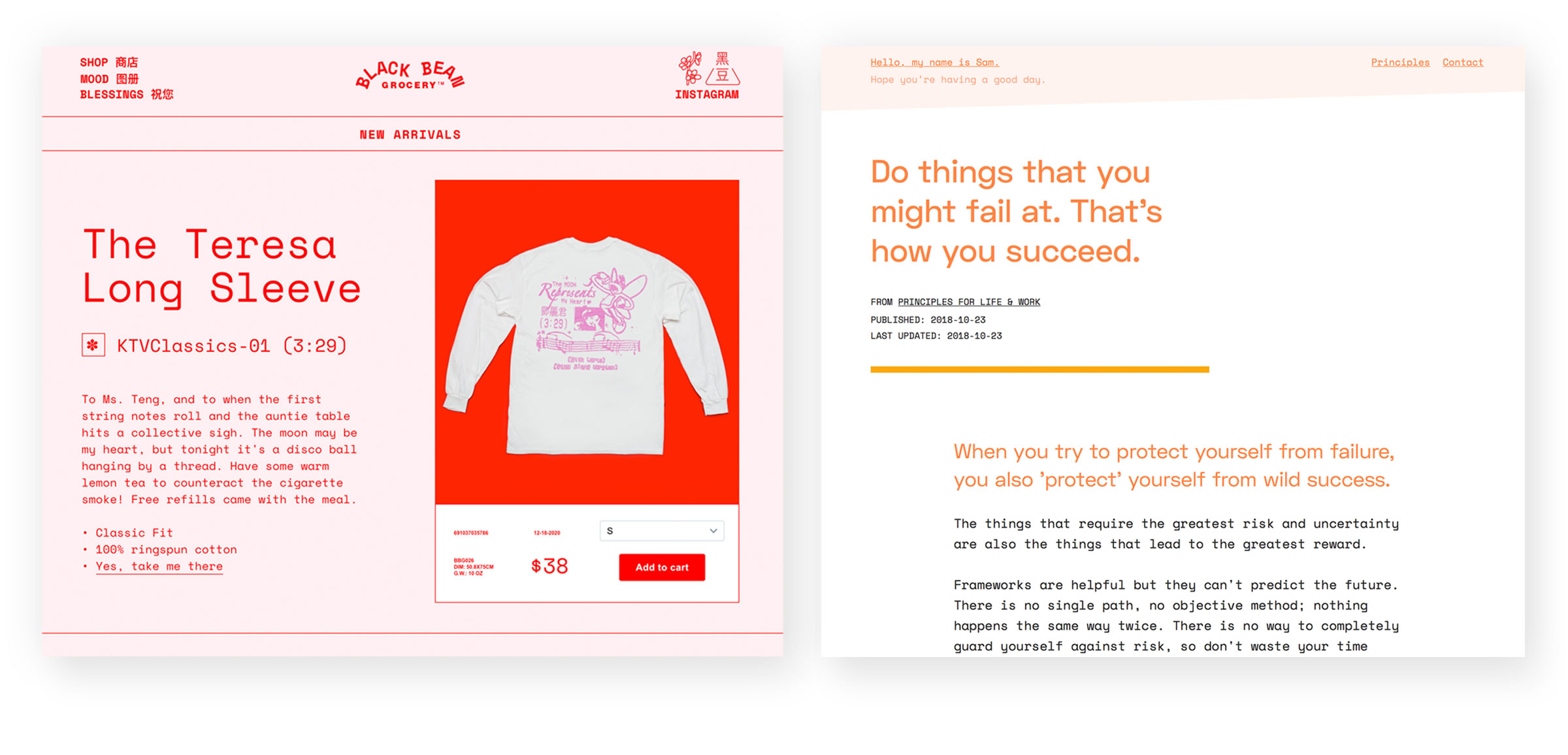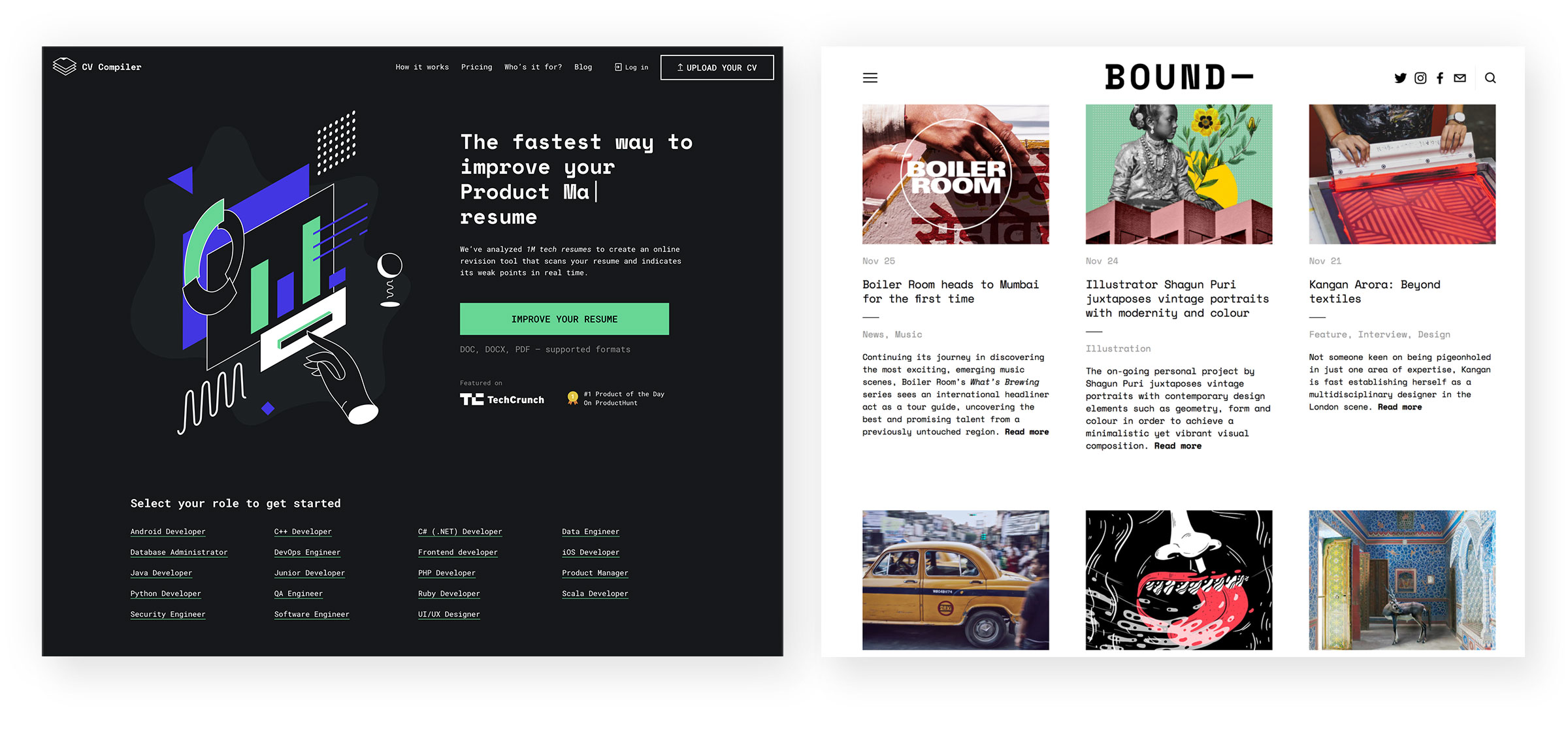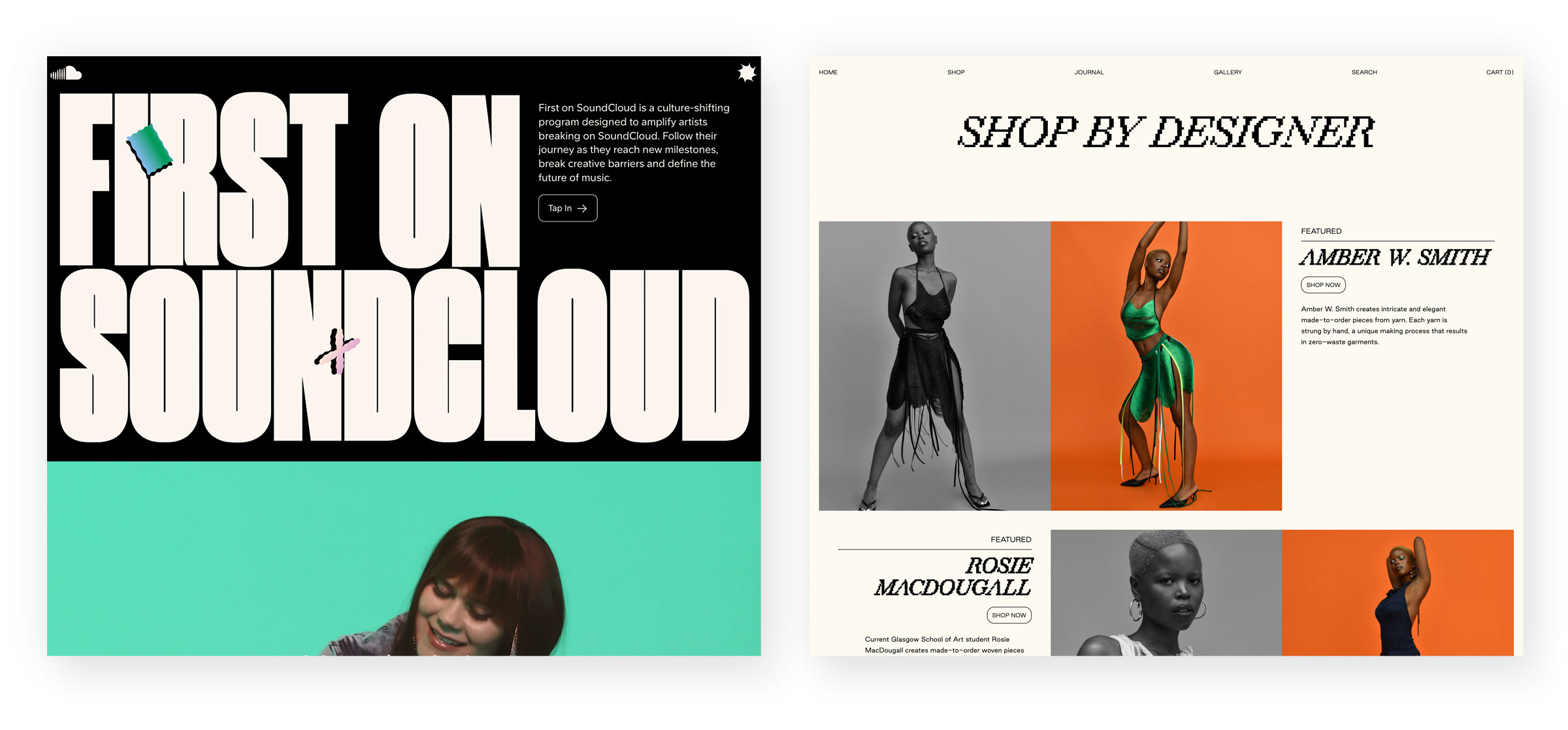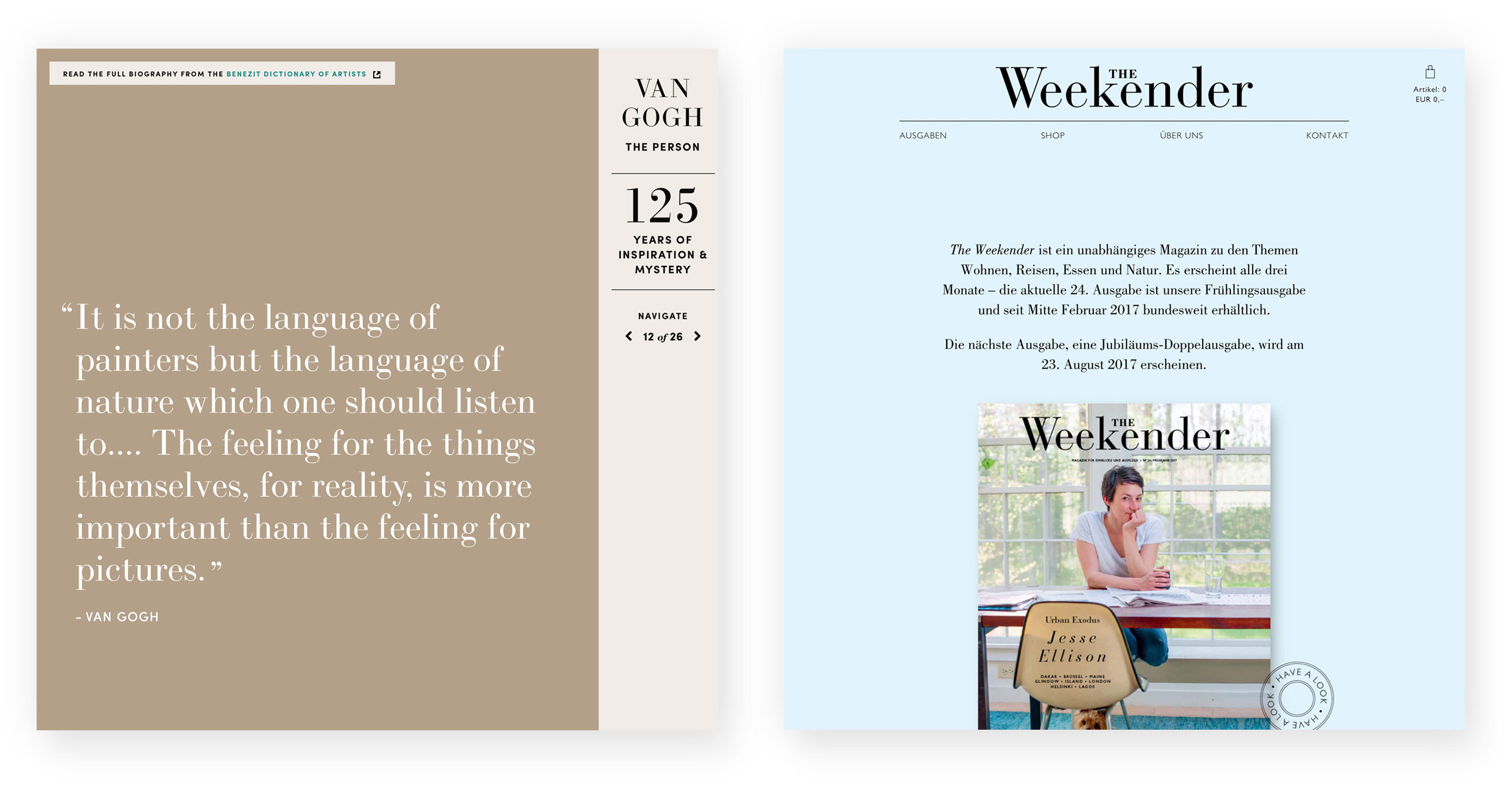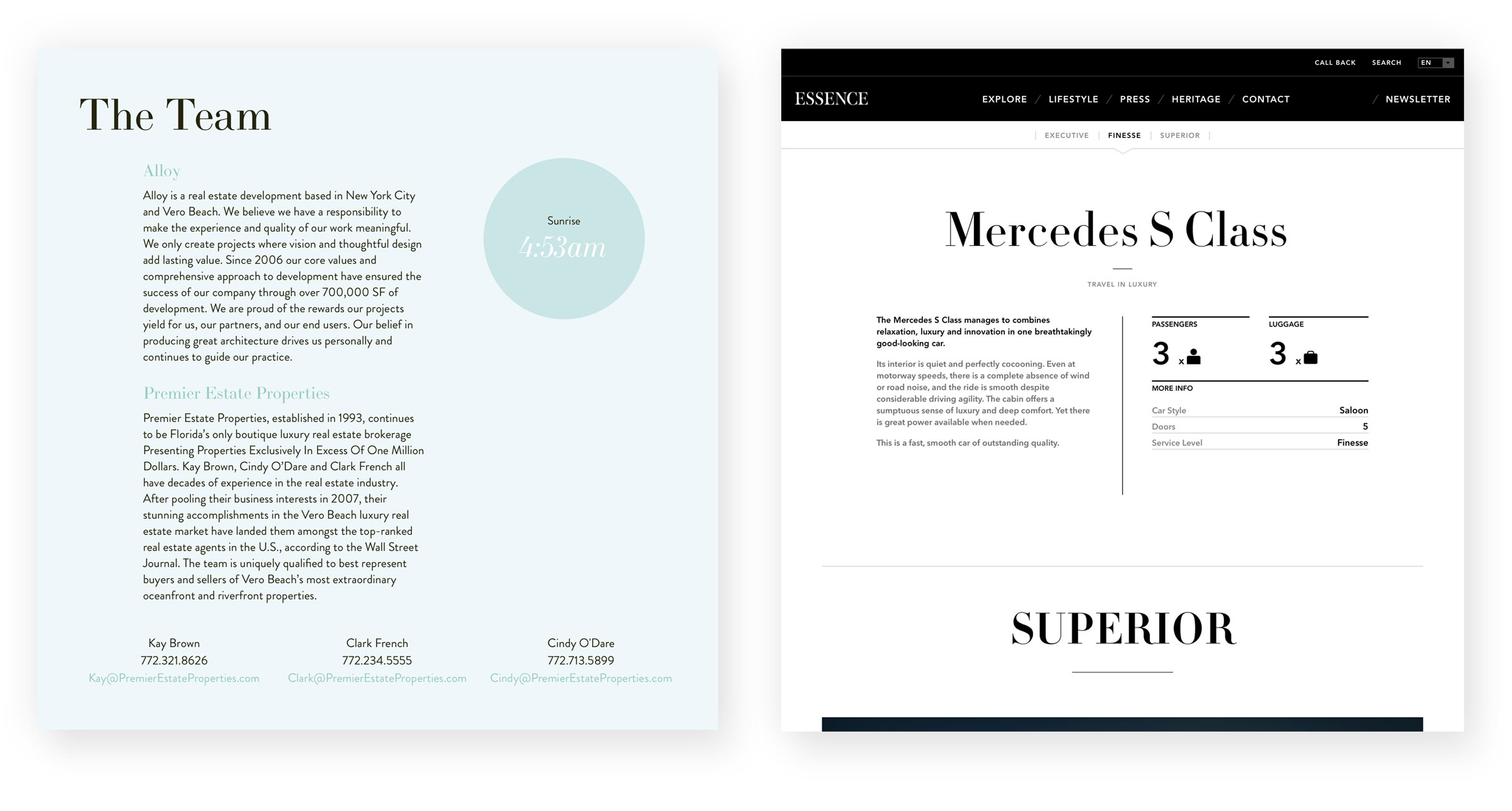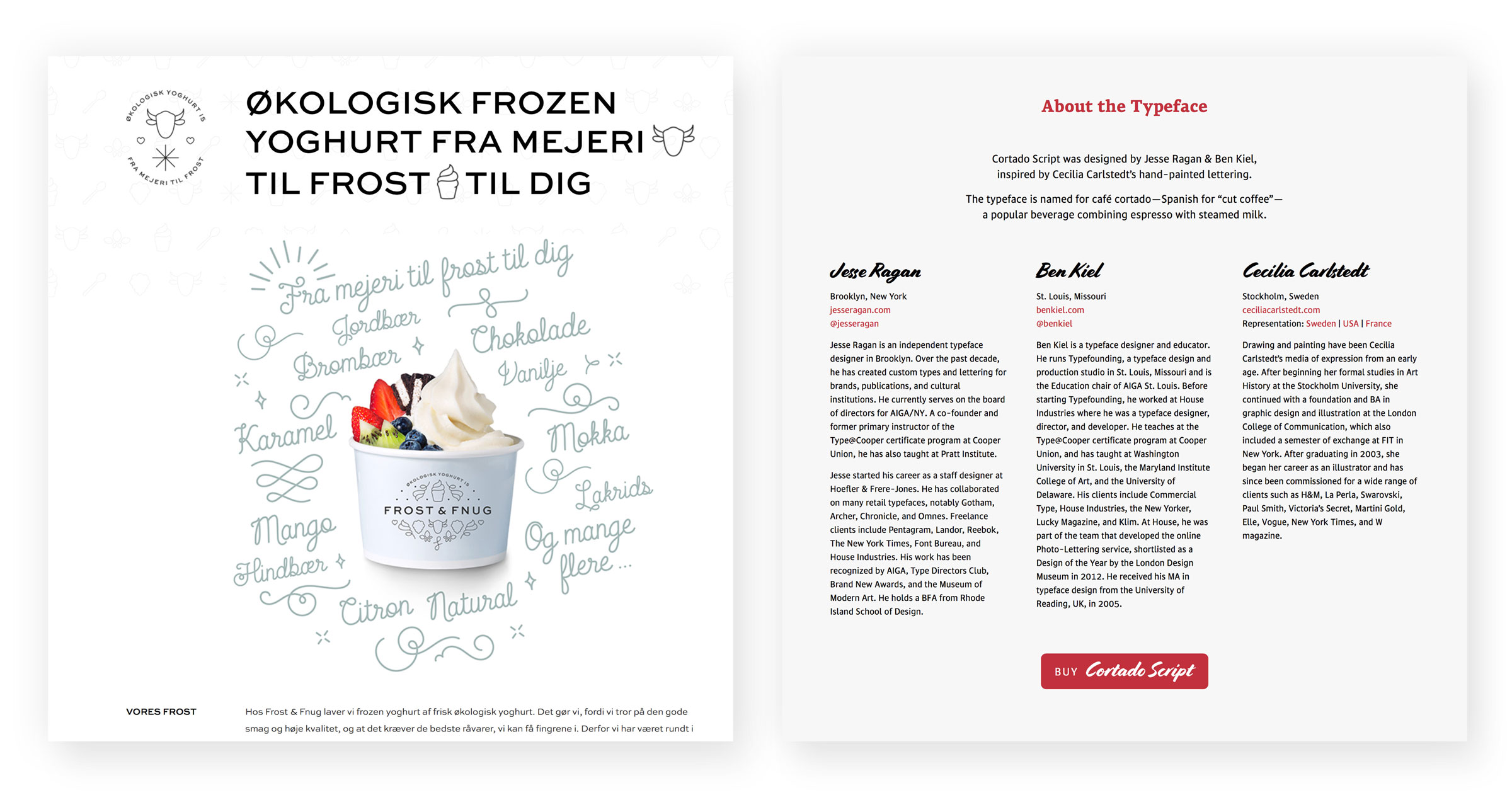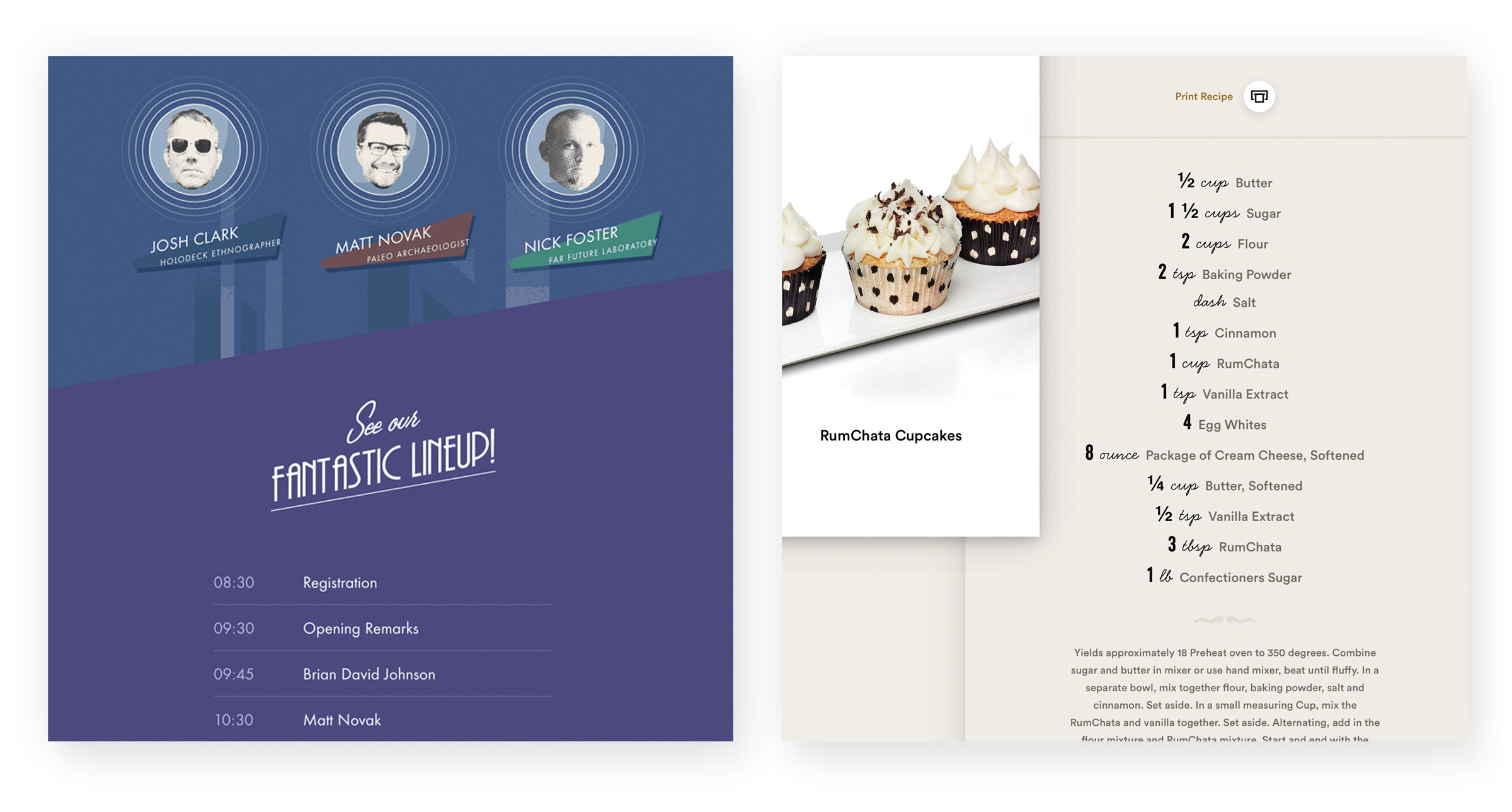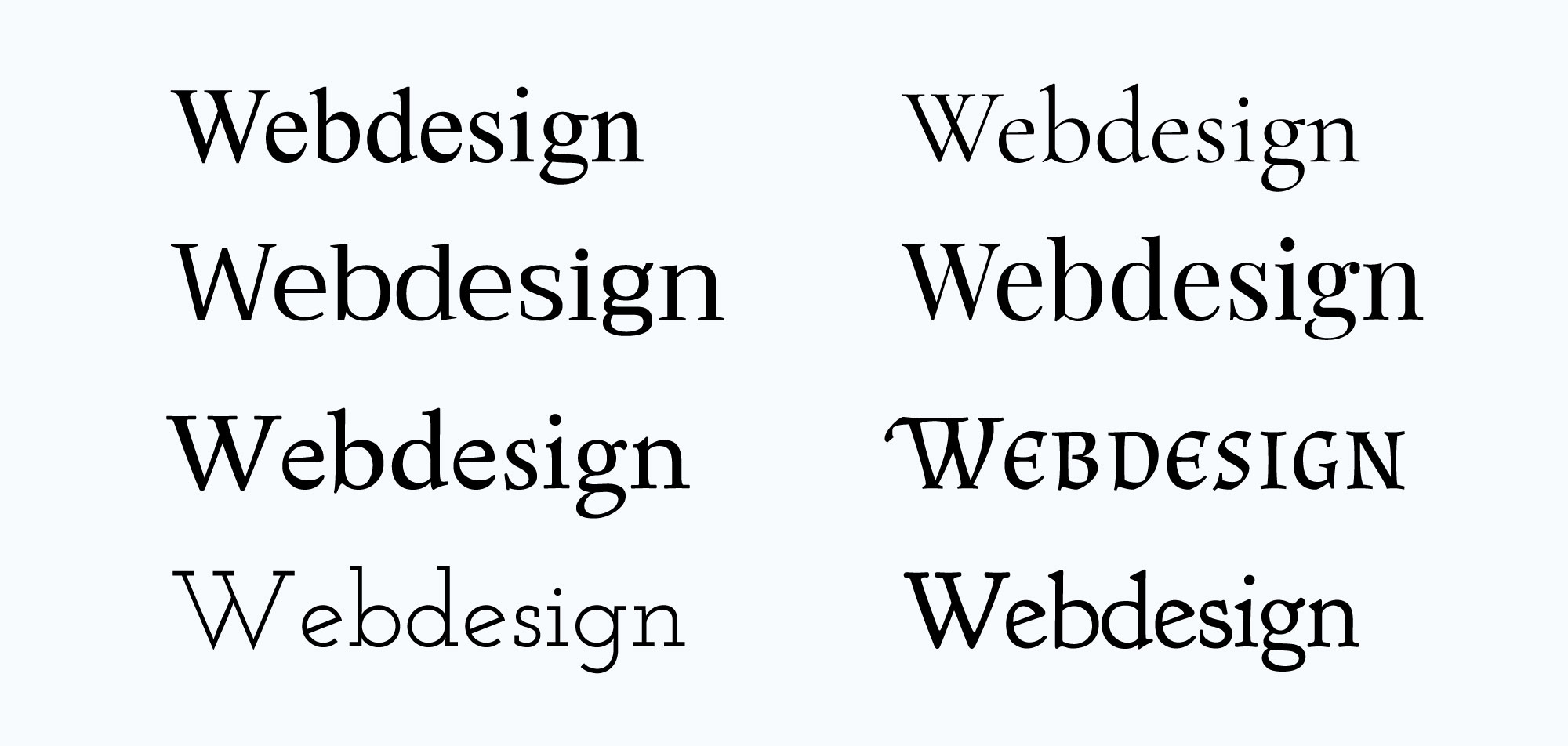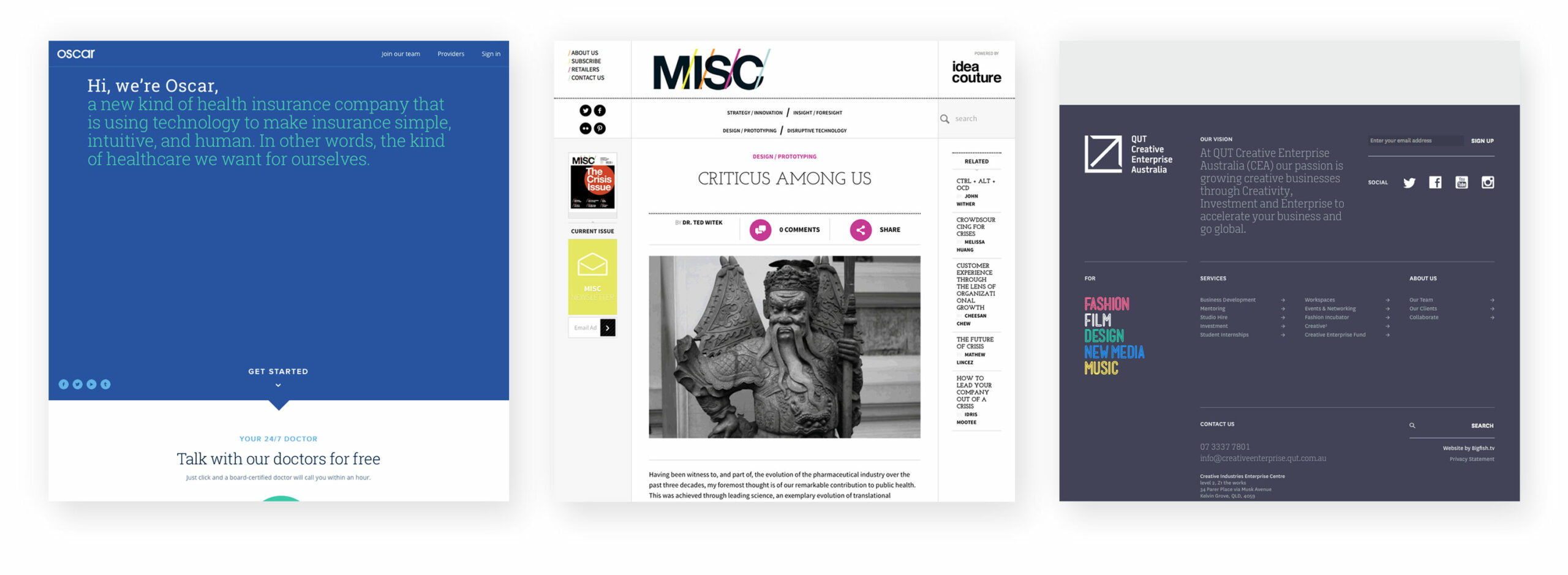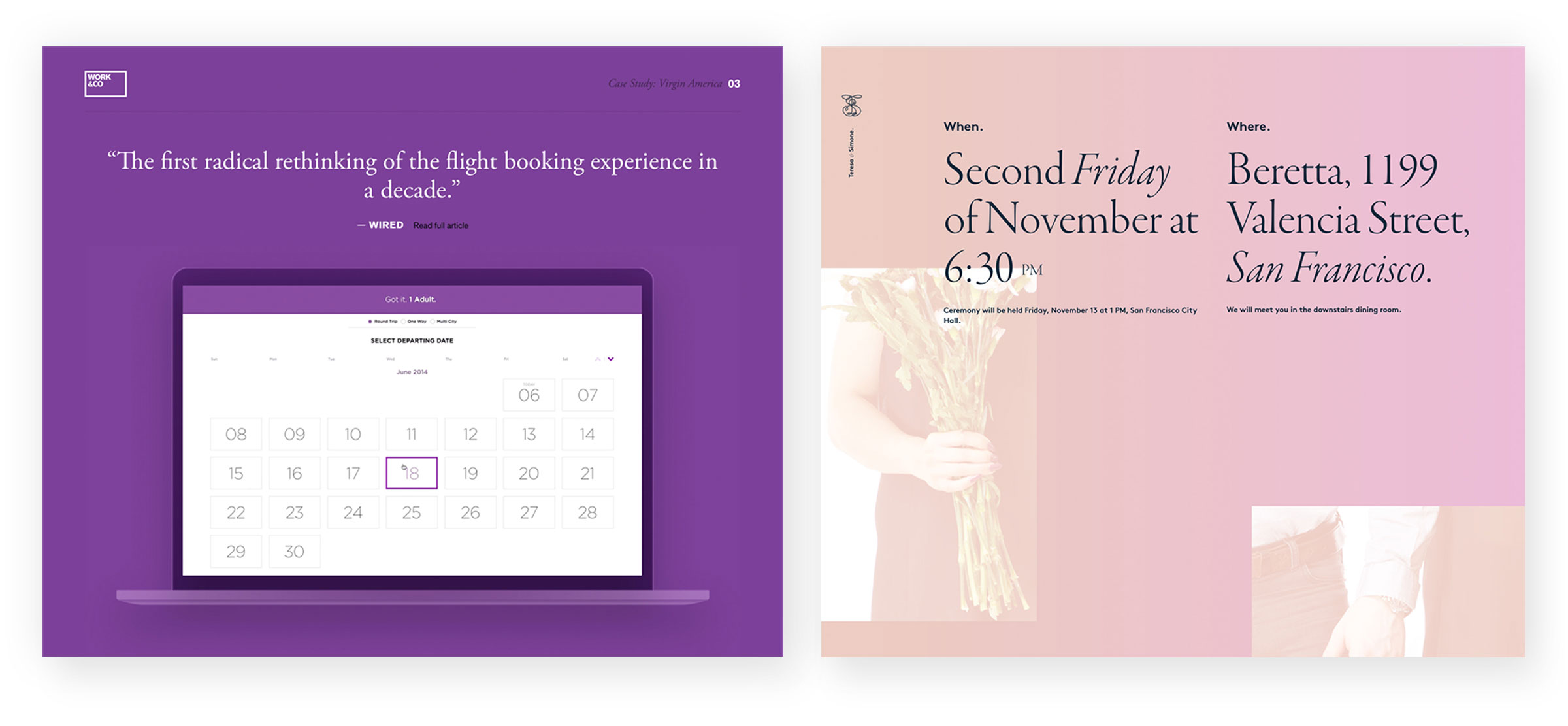
Der ausführliche Überblick
Schriftarten
Auf dieser Seite bekommst du einen umfangreichen Einblick in Schriftarten und deren Einteilung. Ich zeige dir  Einsatzgebiete und viele Beispiele. Zusätzlich erfährst du u. a., wo man Schriftarten finden und identifizieren kann.
Es gibt zigtausende Schriftarten. Um da einen Überblick zu behalten, gibt es sogar eine DIN-Norm (DIN 16518), die diese in elf Gruppen nach bestimmten optischen und historischen Kriterien sortiert. Für den Alltagsgebrauch ist diese Einteilung aber nur bedingt tauglich.
Daher wird gerne ein vereinfachtes System benutzt, das die Schriften zuerst in vier Kategorien eingeteilt, die sich dann auch noch weiter unterteilen lassen:
Das Verständnis der Schriftarten und ihrer Unterschiede ist essentiell, um selber eine gelungene typografische Gestaltung hinzubekommen.
Serifenschriften
Mit Serifen sind diese feinen (manchmal auch dicken) Striche / häkchenartigen Erweiterungen am Buchstabenende gemeint:
Schriftarten – eine Einführung und Überblick 1
Die Serifen sollten dem Auge mehr Halt beim Lesen geben und damit die Lesbarkeit verbessern. Zeitungen und Bücher sind daher meistens in Serifenschriften gesetzt. Serifenschriften werden auch als Antiqua-(Schriften) bezeichnet.
Die verbesserte Lesbarkeit gilt nicht pauschal, sondern hängt im Detail von der Schriftart selber und anderen Einstellungen ab (die Sie im Laufe dieses Moduls noch kennenlernen werden).
Wichtig ist: Die vermeintlich bessere Lesbarkeit der Serifenschriften gegenüber serifenlosen Schriften trifft auf Bildschirmen – und damit im Webdesign – nicht immer zu.
Je nach Bildschirmauflösung verschlechtert sich die Lesbarkeit sogar, da die feinen Serifen nicht gestochen scharf dargestellt werden können.
Die Serifenschriften lassen sich in vier Unterbereiche aufteilen:
Schriftarten – eine Einführung und Überblick 2
Unterschiedliche Serifenschritftarten mit unterschiedlichen Serifenstilen und unterschiedlich guter Lesbarkeit
„Schriftarten mit Serifen haben oft einen etwas distanzierten, institutionellen Beigeschmack.“
Designer Dylan Todd
Klassische Serifenschriften
Diese „old-style“ Serifenschriften wirken sprichwörtlich alt, oder positiv formuliert: traditionell und historisch. Der Übergang zwischen den dünnen und dicken Strichen ist abgerundet:
Klassische Serifenschriftart
Die Garamond als klassische Serifenschrift
Sie vermitteln einen historischen Charme und können durchaus auch in modernen Publikationen zur Anwendung kommen.
In Headlines können die klassischen Serifenschriften ihre volle Wirkung entfalten. Je kleiner der Text, umso weniger sollten sie aber eingesetzt werden.
In Webdesigns vermitteln klassische Serifenschriften meistens einen modernen hochwertigen Stil:
Wirkung klassischer Serifenschriften:
Klassisch, traditionell, stillvoll, hochwertig
Klassische Serifenschriftart
Klassische Serifenschriftarten im UI Design
Transitional Serifenschriften
Transitional Serifenschriften sind den klassischen Serifen ähnlich, nur dass die Enden der Serifen eckig sind:
Schriftarten – eine Einführung und Überblick 3
Sie wirken etwas moderner und leicht mechanisch und dadurch, dass sie nicht mehr so „antiquiert“ wie die klassischen Serifenschriften anmuten, werden sie öfters eingesetzt. Dies liegt auch an der besseren Lesbarkeit auf Bildschirmen.
Typische Transitional Serifenschriften sind z. B. die Times New Roman, Georgia und Baskerville.
Die Transitional Serifenschriften sind so etwas wir der Übergang zwischen den klassischen und den modernen Serifenschriften.
Wirkung transitional Serifenschriften:
Traditionell, erhaben, klassisch, aber gleichzeitig auch modern und hochwertig
Transitional Serifenschriften im Webdesign
Transitional Serifenschriften auf Websites
Moderne Serifenschriften
Diese Schriftarten haben einen starken Kontrast zwischen dünnen und dicken Strichen, dazu keinen abgerundeten Übergang:
Schriftarten – eine Einführung und Überblick 4
Aufgrund des starken Strichstärken-Kontrastes sind diese Schriften weniger gut lesbar und eher nur für Headlines geeignet.
Wirkung moderner Serifenschriften:
Elegant, modisch, kultiviert, zeitlos
Moderne Serifenschriften auf Websites